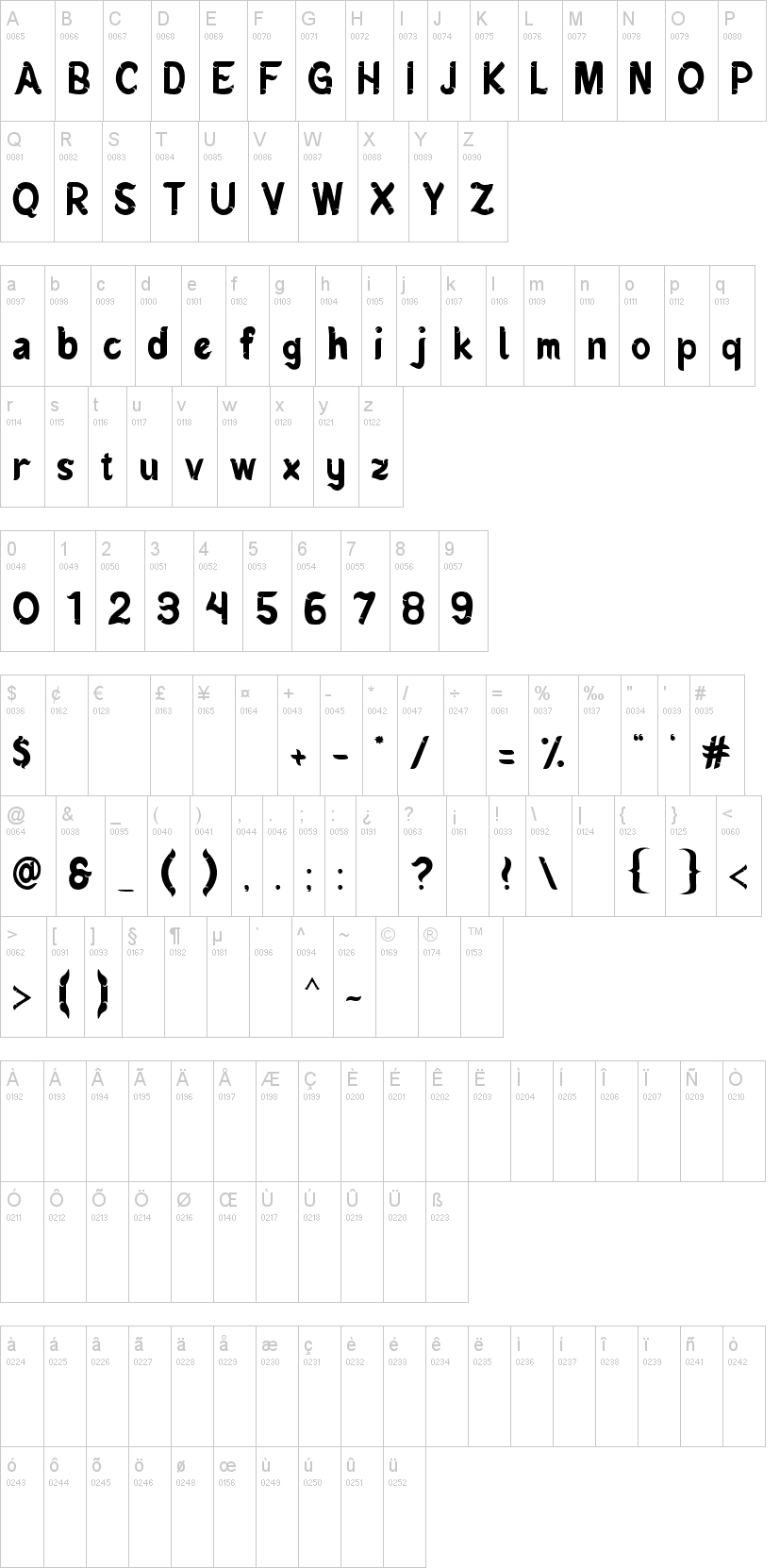
Mendung
Mendung 字体是一款具有独特风格的印度尼西亚字体,它的设计灵感来自印度尼西亚传统的花纹和图案,具有流动的线条,显得更加优雅和精致。它有着平衡的结构,拥有良好的可读性,适合用于新闻、报纸、网站等多种不同的文字场景。
Mendung是一款非常不错的手写艺术字体,具有很好的视觉感,适合于文化类的宣传设计、商业类品牌的广告和产品包装设计以及个性化文字排版等较多场景。
Mendung字符映射图